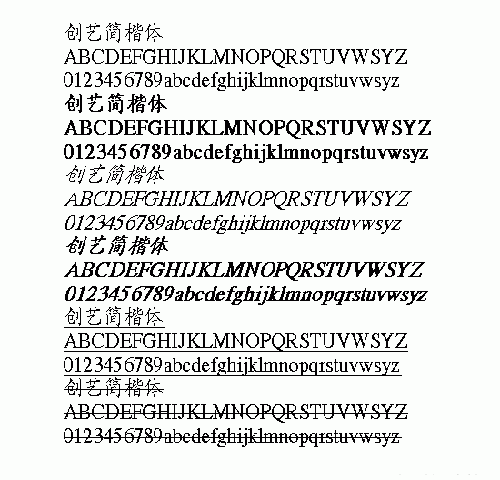
創(chuàng)藝簡楷體字體是一個非常美觀的字體。具備了楷書字體所有特點,同時又帶有藝術(shù)字體的特征??梢杂脕碓O(shè)計廣告等。兼容多種計算機操作系統(tǒng)!歡迎下載使用。
使用說明楷書楷書也叫正楷、真書、正書。由隸書逐漸演變而來,更趨簡化,橫平豎直?!掇o?!方忉屨f它“形體方正,筆畫平直,可作楷?!?。這種漢字字體端正,就是現(xiàn)代通行的漢字手寫正體字。
楷書也是一種官名?!缎绿茣ぐ俟僦径酚浿袝∈佛^有楷書二十人,寫國史楷書十八人??瑫鳛楣倜卜Q作楷書手,掌繕寫之事,在同一機構(gòu)中并置,因具體分工有所不同。《通典·職官二十二》記楷書手為流外勛品官。宋代無楷書手之稱,惟稱楷書。